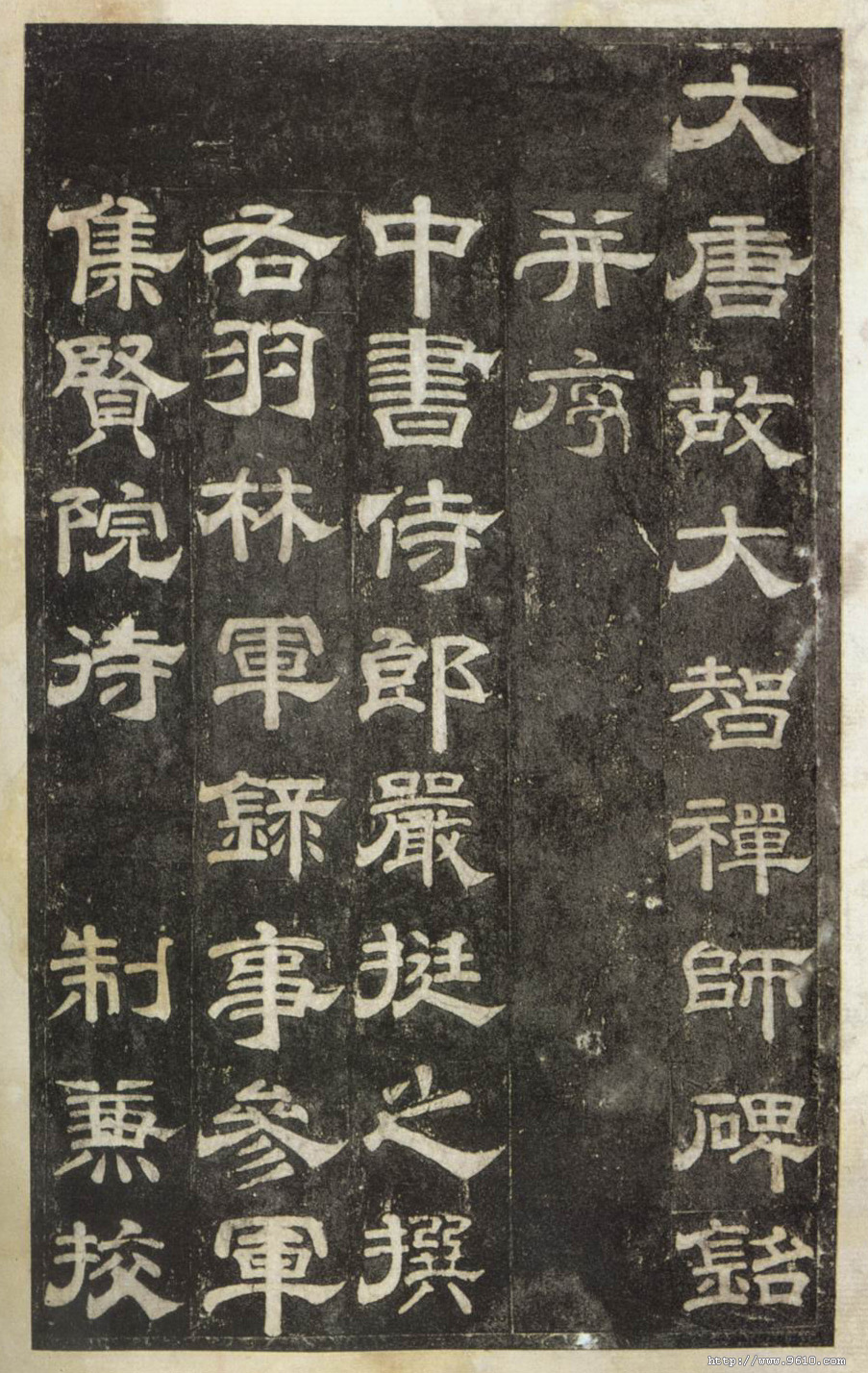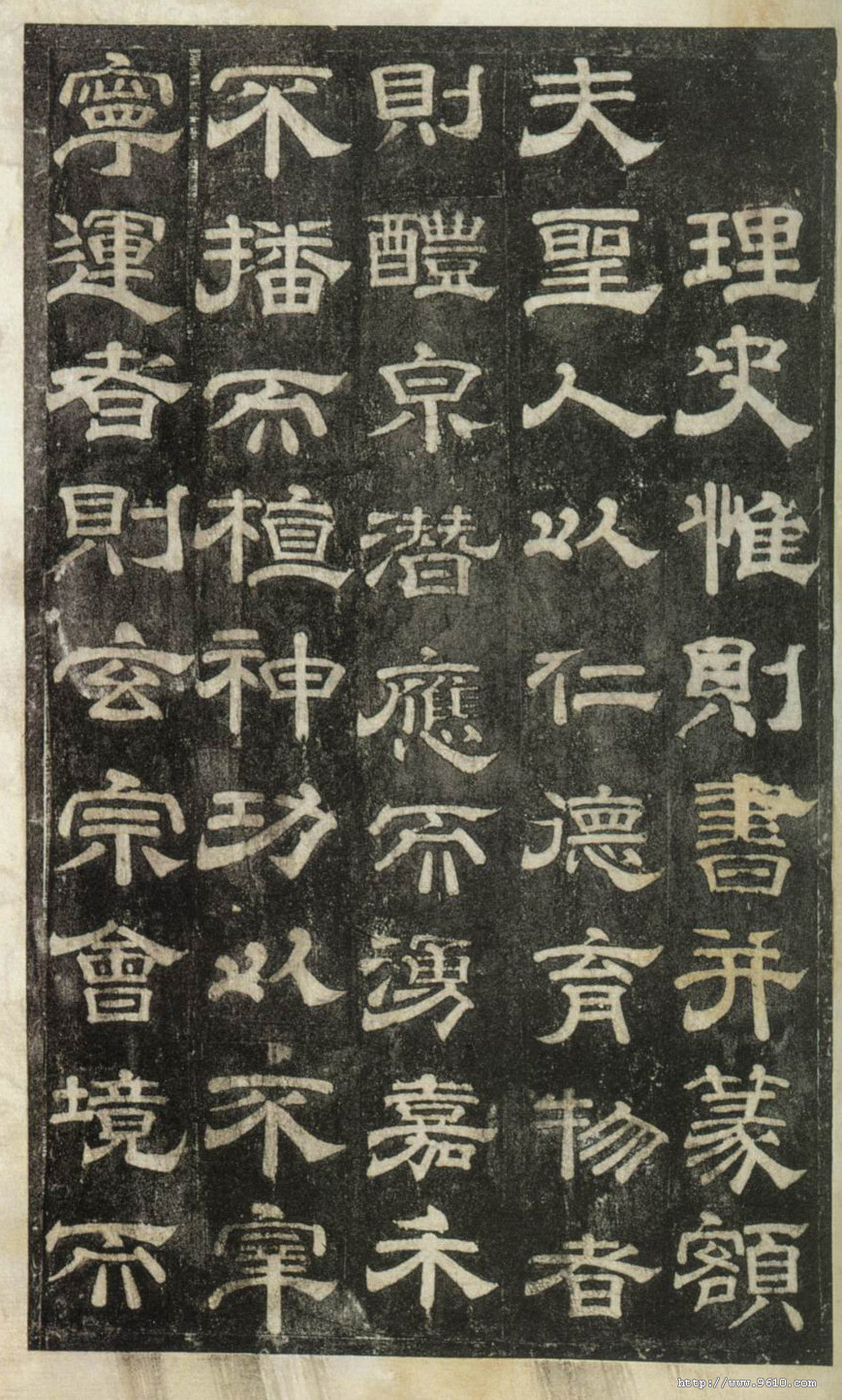
史惟则简介
生卒不详,唐广陵人(今江苏扬州),字向。官至殿中侍御史,人称史侍御。以八分著名,亦工碑额。与韩则木、蔡有邻、李潮并称唐隶四大家。宋陈思《书小史》称其隶书“迫近钟书,发笔方广,字形俊美亦为时重。又善篆籀、飞白”。传世的书迹有《大智禅师碑》等。
作品欣赏:大智禅师碑
《大智禅师碑》唐开元二十四年立,在西安碑林。是著名唐隶碑刻之一。史惟则书。赵明诚评此碑说:“老劲庄严,此书骨力参以和缓之致。”王世贞曰:“惟则《大智禅师碑》、行笔绝类《泰山铭》、而缜密过之。